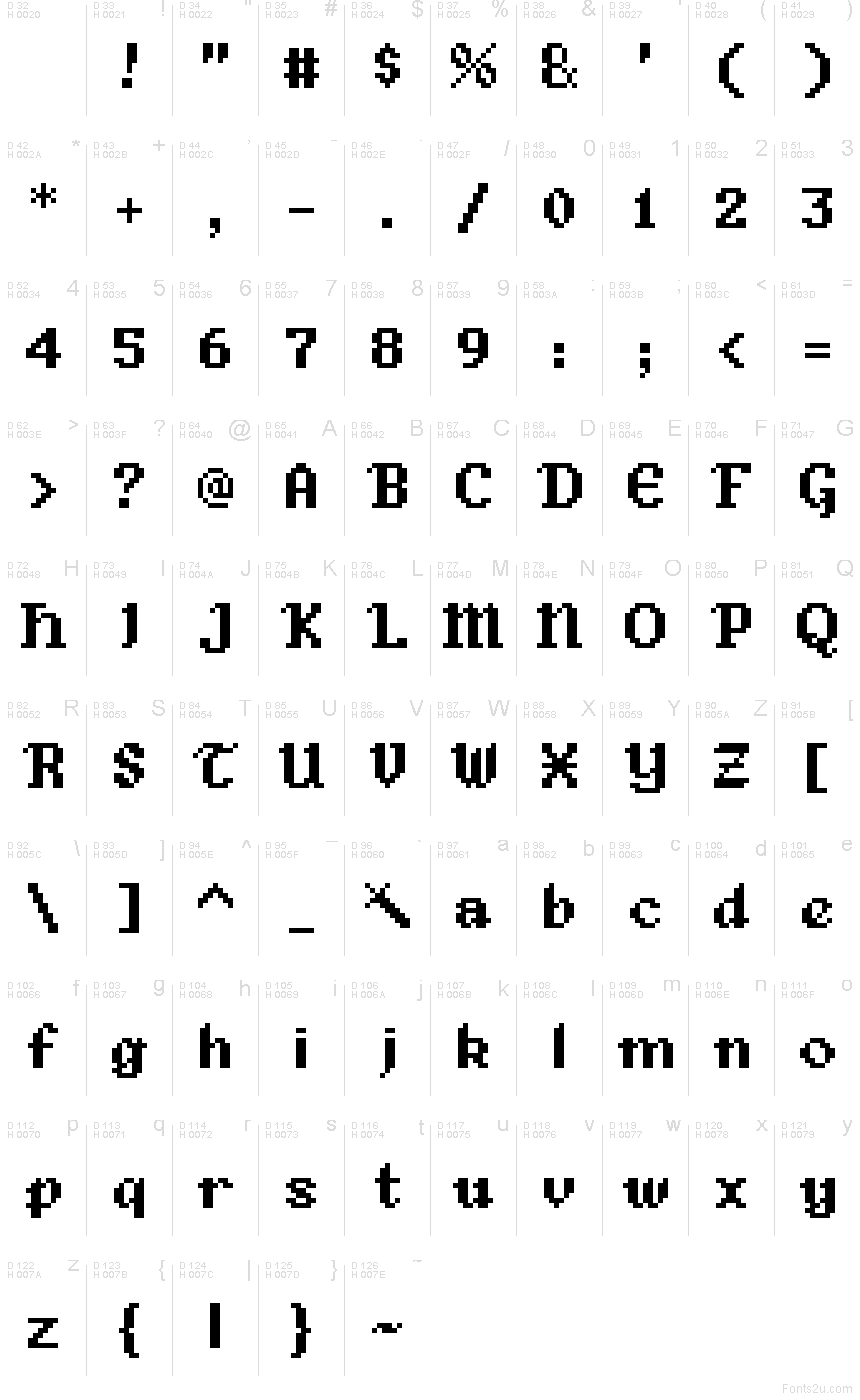
Quill and Antler Expanded od MagicBear je bezplatné pixelové nadpiskové písmo s tupými, blokově stavenými písmeny a úspornou geometrií raného obrazovkového rozhraní. Převládají čtvercové rohy a schodovité okraje, nepravidelné zářezy však udržují tvary živé.
Nezávislé herní studio by jej mohlo použít pro název nebo obrazovkový branding, zejména u projektů s komiksovou, arkádovou nebo záměrně nízkou rozlišovací schopností grafikou. Jeho široké tvary se hodí také na obaly hraček a hravý merchandise, kde mohou písmena fungovat téměř jako řada konstruovaných ikon. Plakáty pro retro herní akce jsou dalším skvělým uplatněním.
„Quill and Antler“ je pixelové písmo s rozšířenou horizontální formou.
Quill and Antler, which is based on Quill and Antler (outdated), which is based on Airmail Fantasy, which is based on Airmail
Designer description: <p>Quill and Antler font with an expanded horizontal form and other alterations.</p>